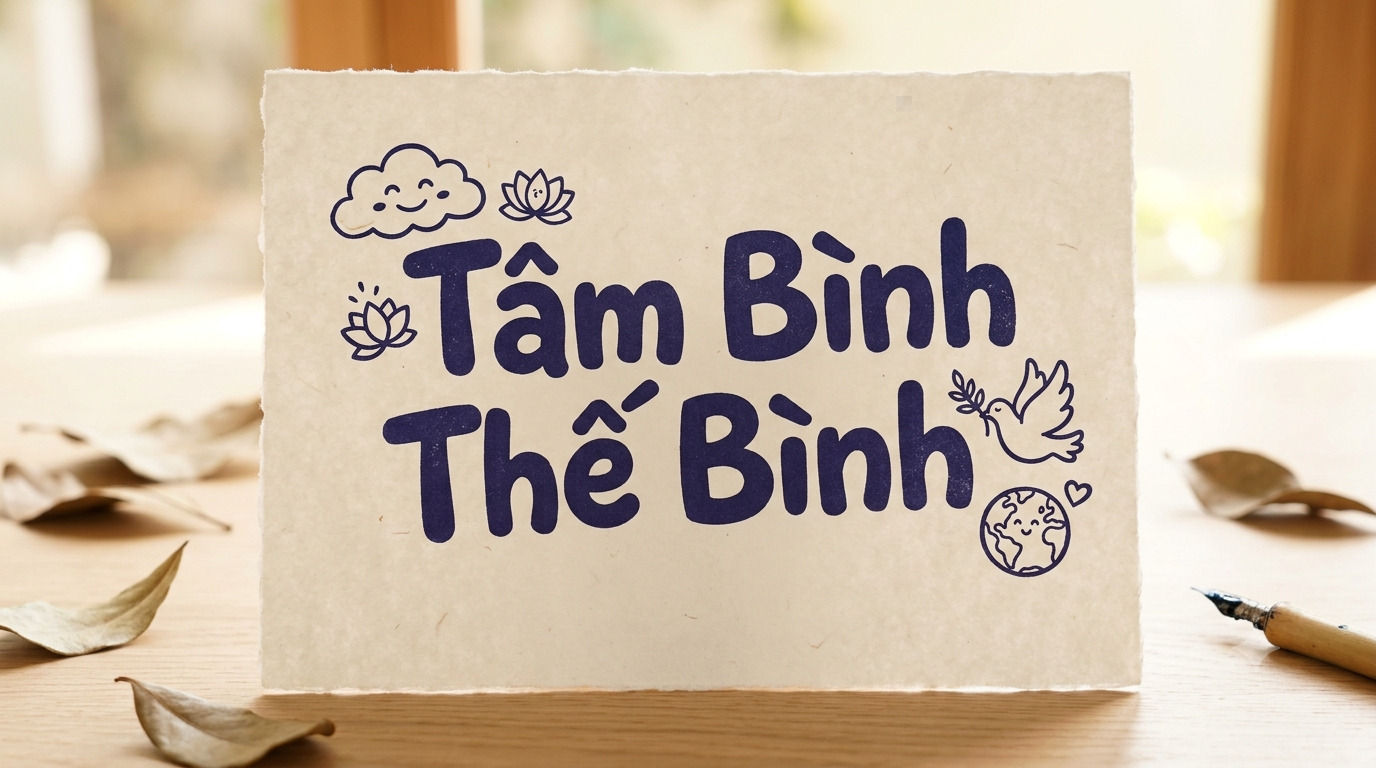
Comic Font là kiểu chữ nổi bật với phong cách vui nhộn, gần gũi và giàu tính sáng tạo, thường được sử dụng trong các thiết kế dành cho trẻ em, sự kiện, bao bì sản phẩm trẻ trung hoặc chiến dịch quảng cáo. Tuy nhiên, nhiều phiên bản font trên Internet chưa được Việt hóa đầy đủ, dễ gặp lỗi thiếu dấu, sai ký tự hoặc mất cân đối khi đưa vào thiết kế.
Font Comic là gì?
Font comic là tập hợp các phông chữ được thiết kế theo phong cách vẽ tay, mô phỏng lại nét chữ trong các cuốn truyện tranh kinh điển. Đặc trưng của dòng phông này là sự vui tươi, ngẫu hứng, nét chữ thường tròn trịa hoặc có độ nghiêng tự nhiên, mang lại cảm giác gần gũi và đầy năng lượng. Đây là sự lựa chọn hàng đầu cho các thiết kế logo ngành giáo dục mầm non, bao bì bánh kẹo, nhãn dán sticker hoặc các poster sự kiện dành cho giới trẻ.
Trong số đó, captain comic font việt hóa nổi lên như một biến thể mạnh mẽ, mang hơi hướng phiêu lưu và hành động. Tuy nhiên, rào cản lớn nhất khi sử dụng các bộ font ngoại nhập này là lỗi gõ dấu tiếng Việt “ư, ơ, đ” bị nhảy font hoặc mất cân đối. Bản việt hóa chuẩn tại In Viva đã được tinh chỉnh kerning hoàn hảo, giúp các ký tự có dấu hiển thị mượt mà trên mọi chất liệu in ấn, từ giấy mỹ thuật đến bình nước nhựa sinh học.
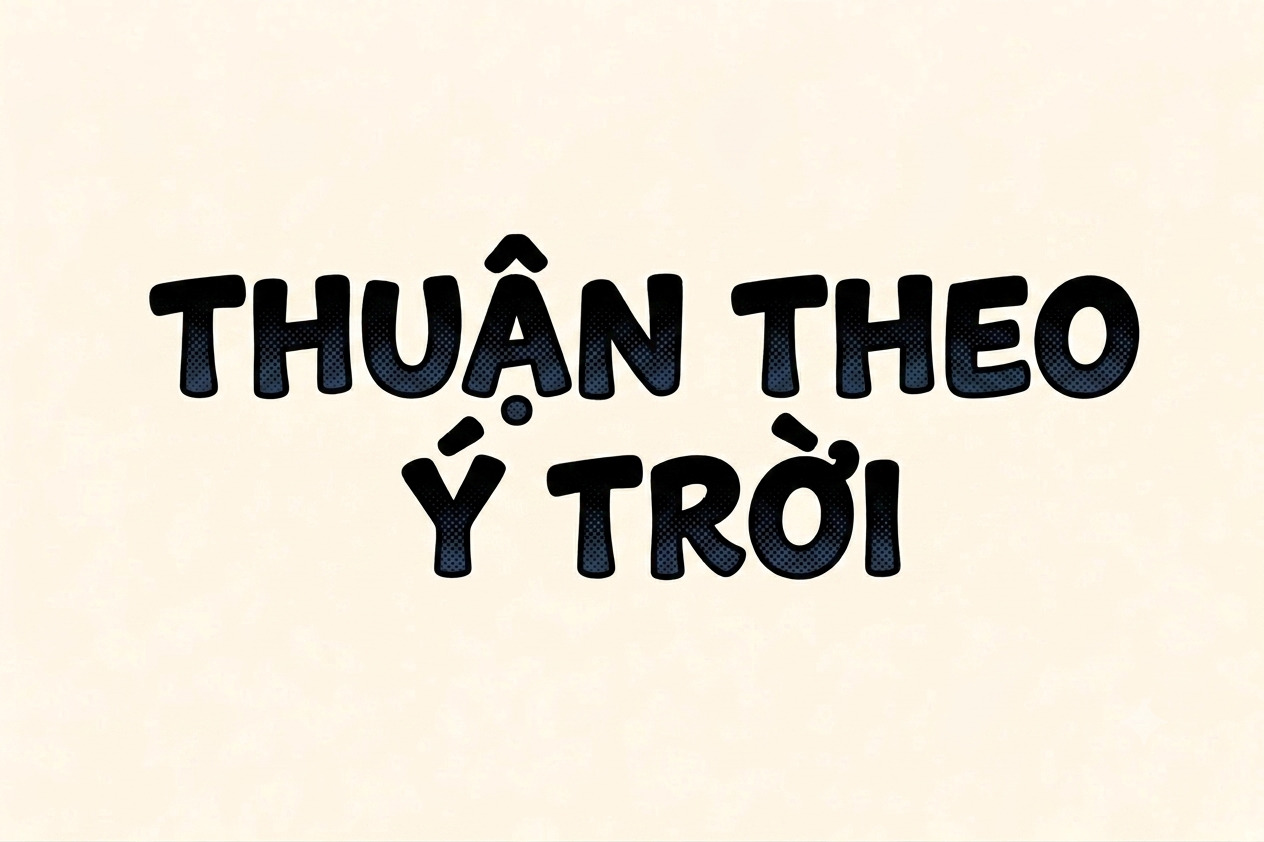
Lưu ý: Khi sử dụng font comic cho các thiết kế hộp quà tặng rực rỡ, bạn hãy phối hợp cùng các bảng màu nóng như đỏ, vàng, cam để tôn lên sự năng động đặc trưng của bộ chữ này.
5 ứng dụng của Comic Font Việt hóa trong thiết kế và in ấn
Với phong cách vui nhộn, gần gũi và giàu tính sáng tạo, Comic Font phù hợp với nhiều sản phẩm bao bì, tem nhãn và quà tặng hướng đến sự trẻ trung, năng động:
- Thiết kế bao bì đồ chơi và bánh kẹo: Comic Font giúp các thông tin trên hộp giấy, bao bì sản phẩm trở nên sinh động, thu hút trẻ em và tạo cảm giác vui vẻ ngay từ ánh nhìn đầu tiên.
- Sản xuất sticker và tem nhãn sản phẩm: Kiểu chữ viết tay của Comic Font phù hợp với nhãn vở, sticker trang trí hoặc tem nhận diện, giúp thiết kế trở nên gần gũi và nổi bật hơn.
- In áo thun, nón và quà tặng sự kiện: Comic Font khi in chuyển nhiệt trên đồng phục, nón hoặc vật phẩm quảng bá giúp thể hiện phong cách cá tính, năng động cho các chương trình, hoạt động tập thể.
- Thiết kế backdrop và banner sự kiện: Với file vector sắc nét, Comic Font có thể phóng lớn trên các ấn phẩm sự kiện mà vẫn giữ được đường nét mềm mại, hạn chế vỡ hình khi in kích thước lớn.
- Thiết kế bao bì túi giấy ngành giải trí: Font Comic phù hợp với các mẫu túi giấy đựng quà sự kiện, sản phẩm game, phim ảnh hoặc thương hiệu trẻ trung nhờ khả năng tạo điểm nhấn vui nhộn và khác biệt.
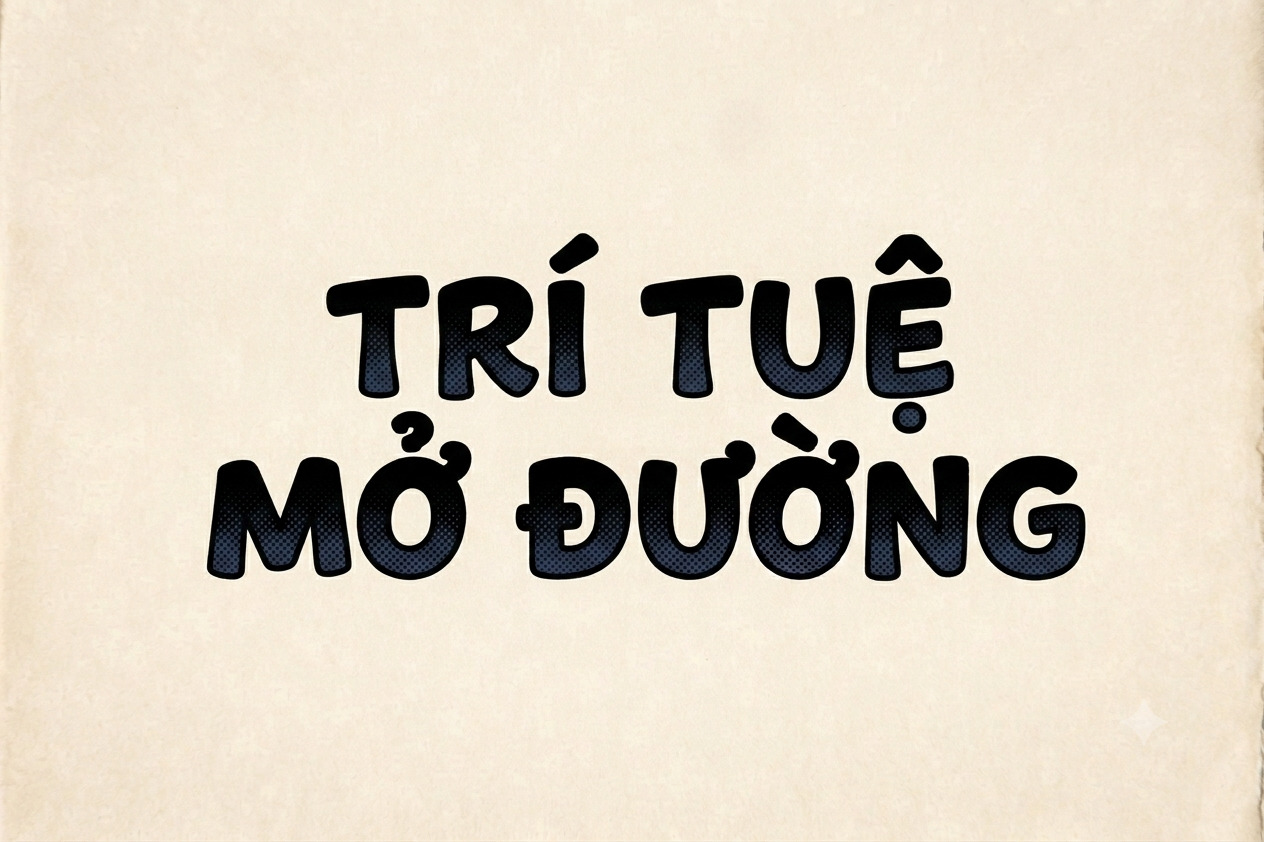
4 lưu ý khi sử dụng font Comic Việt hóa
Để font Comic Việt hóa giữ được phong cách vui nhộn, rõ nét khi ứng dụng vào thiết kế và in ấn thực tế, designer cần chú ý các yếu tố sau:
- Kiểm soát khoảng cách giữa các ký tự: Font Comic thường có nhiều nét bo tròn và chi tiết nhỏ. Khi in tem nhãn hoặc sticker kích thước nhỏ, cần điều chỉnh khoảng cách chữ phù hợp để tránh tình trạng mực bị dồn, làm mất độ rõ nét.
- Tối ưu đường Path khi gia công bế nổi: Chuyển đổi font Comic sang dạng vector giúp các đường nét minh họa được giữ chính xác khi gia công. Đặc biệt với logo hoặc tên thương hiệu trên hộp quà, kỹ thuật này giúp hạn chế lỗi răng cưa, sai lệch khi dập nổi.
- Lựa chọn lớp phủ bảo vệ phù hợp: Với các thiết kế sử dụng màu sắc tươi sáng của Comic Font, nên kết hợp cán màng bóng hoặc phủ bảo vệ để tăng độ nổi bật, đồng thời hạn chế trầy xước trong quá trình sử dụng.
- Kiểm tra màu sắc trước khi in: Cần thiết lập hệ màu CMYK phù hợp để các màu sắc đặc trưng của phong cách Comic như đỏ, vàng, xanh giữ được độ tươi sáng khi in trên hộp giấy, bao bì hoặc vật phẩm quảng bá.